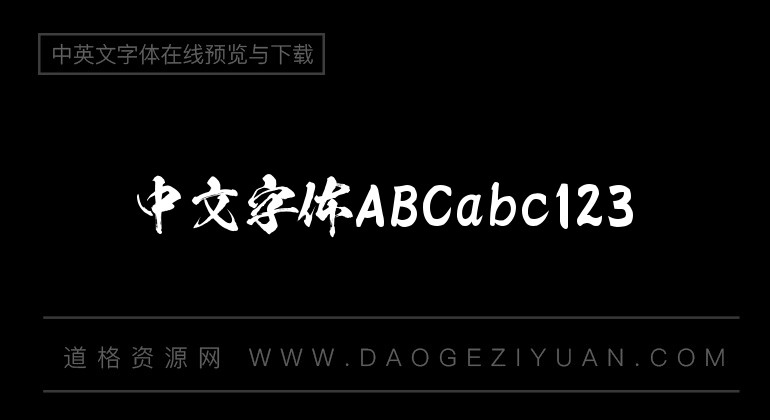
字形清新飘逸,笔画间的游丝恍若进入了一种微醺状态。笔墨线条的轻重缓急、粗细对比强烈,字的重量集中分布在某几个笔画上,着重突出表现,其他的笔画则纤细轻柔。每个字的折笔既有顿笔处理,也有圆转处理,细节丰富,变化多端。字面宽大,中心一致,视觉上整齐划一
和风书道昭和黄龙是一款具有浓郁日式风格的书法字体。该字体的设计灵感来源于日本的昭和时期和黄龙,采用了典雅的日本笔法,字形刚柔相济,既有端庄的气质,又富有流畅的韵味,展现出了日本传统文化的独特魅力。
和风书道昭和黄龙的字形特点是线条流畅、简洁,形体刚柔相济,端庄大气。该字体采用了传统的日本笔画技法,特别是在筆画的起筆、中止、轉折和線條的厚薄變化上,具有明顯的特色。整体风格典雅,适合用于日式风格的设计,如宣传画、海报、广告等。
和风书道昭和黄龙的设计理念是融合中日文化,表达出和风书道精神。在设计上,字体采用了日本书法的笔画技法,同时结合了中国书法中的一些元素,呈现出独特的创意和风格。这种设计理念与当今强调文化融合、跨文化交流的价值观相契合,因此备受广大设计师和广大用户的青睐。
总的来说,和风书道昭和黄龙是一款充满浓郁日式风格的书法字体,其字形优美流畅,端庄大气,展现出了日本传统文化的独特魅力。它的设计理念融合了中日文化,表达出了和风书道精神,与当前推崇文化融合、跨文化交流的时代精神相符合,是非常值得推荐的字体之一。
和风书道昭和黄龙免费字体下载是一款非常不错的手写艺术字体,具有很好的视觉感,适合于文化类的宣传设计、商业类品牌的广告和产品包装设计以及个性化文字排版等较多场景。